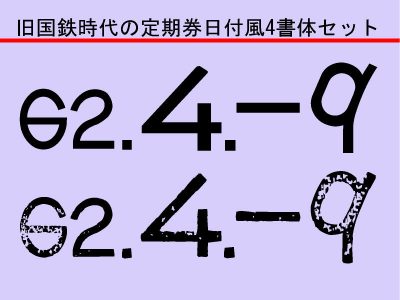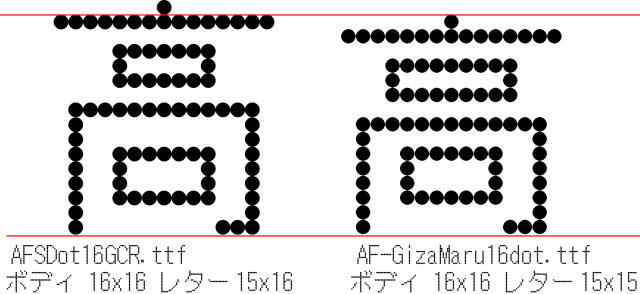
1960年代から見かけるユーロスタイル風なサンセリフ、1Byte 欧文デザインフォントです。
74.テロップ専用復刻欧文AF-TelopBod
AFSBoを横に太くしたウエイト違いの欧文フォントです。縦横の差を大きくしコントラストを強くし見出し用としてインパクトを与えます。大見出し、動画サムネイルにフィットします。
73.AF-篆書 04DB 3 書体セット
AFSTenduex04Rのウエイトを太めにしファッション誌の見出し、小仮名版は可読性が変化する事でMusicvideoの歌詞テロップに効果を与えます。篆書体をベースにしていますが一般的な長体の篆書体とは違い仮想ボディを正方形にしたデザインです。篆書と言えば縦組みですが横組みに最適化されているモダンな篆書体。アイキャッチ用として利用する事を目的にしました。
72.ストックカーレーシングみたいな欧文
アメリカはストックカーレーシングでレースカー側面に貼られる数字や文字を模した1Byte欧文デザインフォント。AP機能の関わらず左右斜体が利用できる便利なセットです。アプリケーションソフト利用はもちろん、動画テロップ後の配信、字形装飾が困難なWeb Serverへのアップ、PDFエンベッド、各種商用利用できます。
71.まんが/アニメ Web 動画 アンチックインパクト
個人同人作家に最適、漫画・ラノベ・コミック等の動画テロップやサムネイルに最適なアンチック体。小仮名版は、ひらがなとカタカナを90%に設定。インパクトある文章に冴えます。
・ベースフォント
漢字:極太ゴシックの「AF-UVImpact.ttf」動画テロップ用に作成された極太フォント。ひらがなとカタカナは明朝系「AFSミンフォーマル」。
70.テロップ/サムネイル用 AF-UVImpact
数字や平仮名字形はUD フォントに利用される視認性のよい字形。大きく太く目立って読みやすい書体は、動画編集時袋文字などへの加工する必要のない目立つデザインです。
特徴が顕著に表れる一部の英数字ひらがなカタカナを一般的な UD フォントに近づけると共に、ひらがな字形ついては学参フォントを意識し視認性を強化しました。当製品は「AFSGothicView」ファミリを元に作られEよりも太めなウエイト違いです。
69.ロゴ用欧文フォント 10書体セット
半角アルファベット大文字小文字と数字からなる欧文フォントでやや太めのウエイトにデザインされました。
68.ロゴ製作用 素材欧文フォント 10書体セット
半角アルファベット大文字小文字と数字からなる欧文フォントでやや太めのウエイトにデザインし合字にもご利用頂けるようスタンダードなデザインフォントでまとめました。
67.デコレーション用欧文フォント 5書体セット
見出し小見出しなどアイキャッチ用に可愛らしさと愉しさを求める場所にご利用ください。太めの欧文デザインフォント、5書体セットです。
66.欧文・US フリーウェイのLED SIGNみたいなフォント4書体
アメリカのハイウェイに設置されている電光掲示板に見られるドット表示の欧文を模したTTF(True Type Font)です。デジタル初期にあるレトロゲームなイメージから本格的なディスプレイまでご利用頂けます。欧文フォント2 サイズ、それぞれ固定幅とプロポーショナル合計4 書体セットです。
65.欧文アニマルシリーズ5書体セット
地に足がつくフォントに動物(くま、ねこ、うし、いぬ、うさぎ)を模したシルエットを一部文字に埋め込みました。ベースフォントは安定性や信頼性を醸し出すデザインでロゴや見出しに最適な[AFSClar]を流用しました。可愛い愉しいロゴなど遊び心を演出する欧文フォントです。
64.ユニバーサルフォント AF-UniversalView
元祖UDフォントのメイリオを源流とするAFSGothicViewシリーズを強化。UDフォントの特徴が顕著に表れる「ひらがな、カタカナ、英数字」をブラシアップしました。
1)当製品は、元祖ユニバーサルデザインフォントであるメイリオを源流にもつゴシック体フォントです。特徴が顕著に表れる一部の英数字ひらがなカタカナを一般的なUDフォントに近づけると共に、ひらがな字形ついては学参フォントを意識し視認性を強化しました。
2)当製品は「AFSGothicView」ファミリを元に作られました。全角(2Byte)漢字に差異はありません。
63.シリーズ「ギザかく/ギザまる」
ビットマップフォントのデザインを模したアウトラインフォントです。一見するとギザギザな■や●で構成されたドットフォントですが、アウトラインがしっかりしたTTF(TrueTypeFont)フォーマットで他の書体同様に扱いが簡単です(woff版も同時発売)。ガラケー風やPOSレジのレシートみたいな小さなサイズから鉄道の行き先案内である発車標みたいなデザインまで見た人にイメージを与えられるデザインフォントです。カメラのファインダー、各種端末、リモコン、AV機器、電光ニュース、制御パネル表示をイメージ演出させやすいドットデザインです。
ガラケー文字みたいな「AF-GizaKaku12dot」「AF-GizaMaru12dot」
マイコン時代みたいな「AF-GizaKaku14dot」「AF-GizaMaru14dot」
レシート印字みたいな「AF-GizaKaku16dot」「AF-GizaMaru16dot」
ワープロ印字みたいな「AF-GizaKaku20dot」「AF-GizaMaru20dot」
鉄道発車標みたいな「AF-GizaKaku24dot」「AF-GizaMaru24dot」
弊社近似製品「AFS ゴシック■16R」「AFS ゴシック●16R」とはレターサイズが異なります。
AFS ゴシック■16R.ttf、 AFS ゴシック●16R.ttf (ボディ16×16 レター15×16)
AF-GizaKaku16dot.ttf、AF-GizaMaru16dot.ttf (ボディ16×16 レター15×15)
1)字形デザイン ビットマップフォント風
・令和合字
当フォトは令和合字に対応しユニコードの[32FF]に収録さいます。
62.定期券日付風数字
鉄道定期券の日付を模した数字フォント。セキュリティ面においても他デザインとは類似性が低く、日付に限らずシリアル番号など実用的なご利用も可能です。ユニークな形状である定期券日付数字はマニア心をくすぐります。
51.AFS型抜きスリット
AFS型抜きスリットは、オリジナルフォントの輪郭を残し、スリット状の型抜きで刻み文字を作成しました。大きなサイズの印刷表示でもくどさを感じさせずにインパクトを与えることができます。単色印刷のバックグラウンド、セキュリティを意識したウォーターマーク(透かし)、強調用にご利用ください。